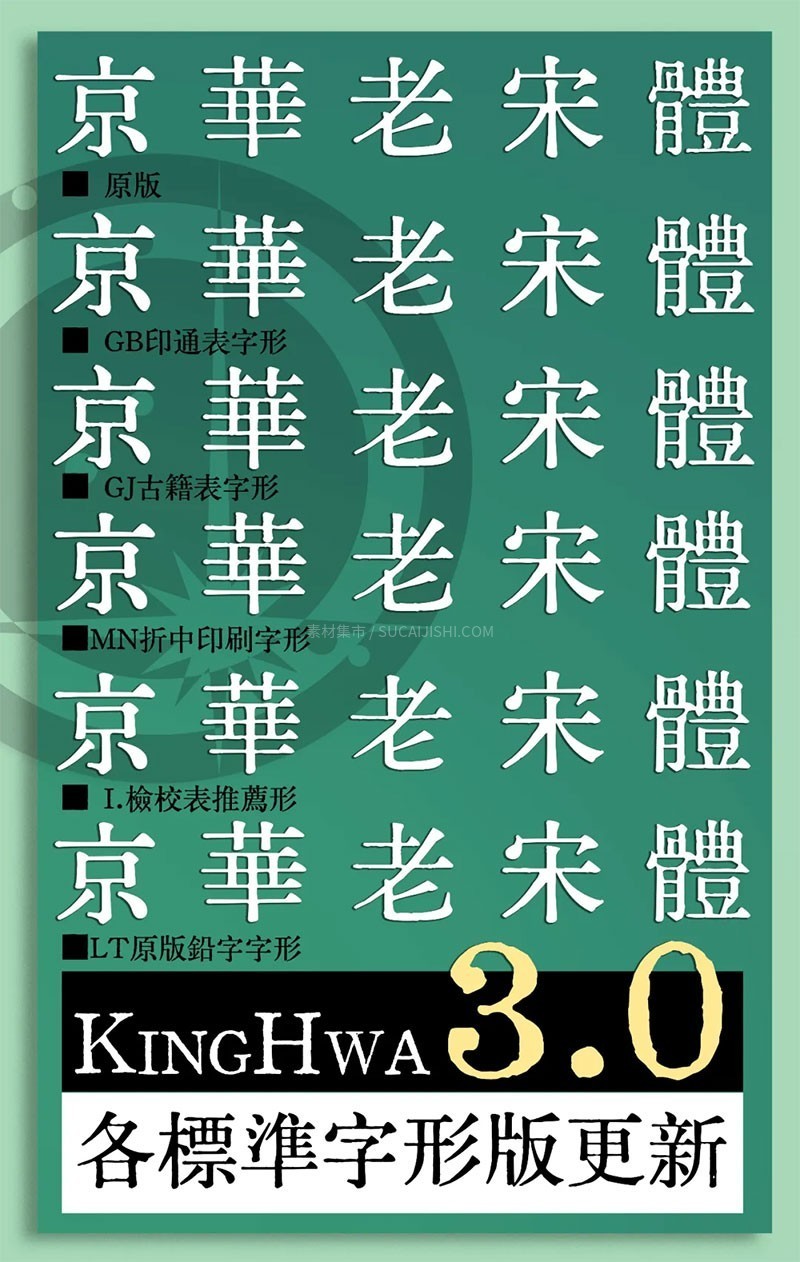
京华老宋体(KingHwa_OldSong)是一款免费商用的中文字体,由知乎网友(id:特里王)利用AI技术辅助生成。其风格来自于1961年北京新华字模厂改刻的老筑地体61-1体,具有桃形点、鹅头勾和三角字肩等老宋体的特点,比现今常用的宋二体更加厚重圆润,基本还原了60年代左右的印刷风格。
与「汇文明朝体」相比,京华老宋体更接近现代排版的风格,排版效果更加工整秀丽,少了一些破落、古拙的质感,多了一些标致、正规的气息。如果您正在寻找一款老宋体风格的字体,不妨尝试一下京华老宋体,它将为您的设计作品增添独特的艺术魅力。